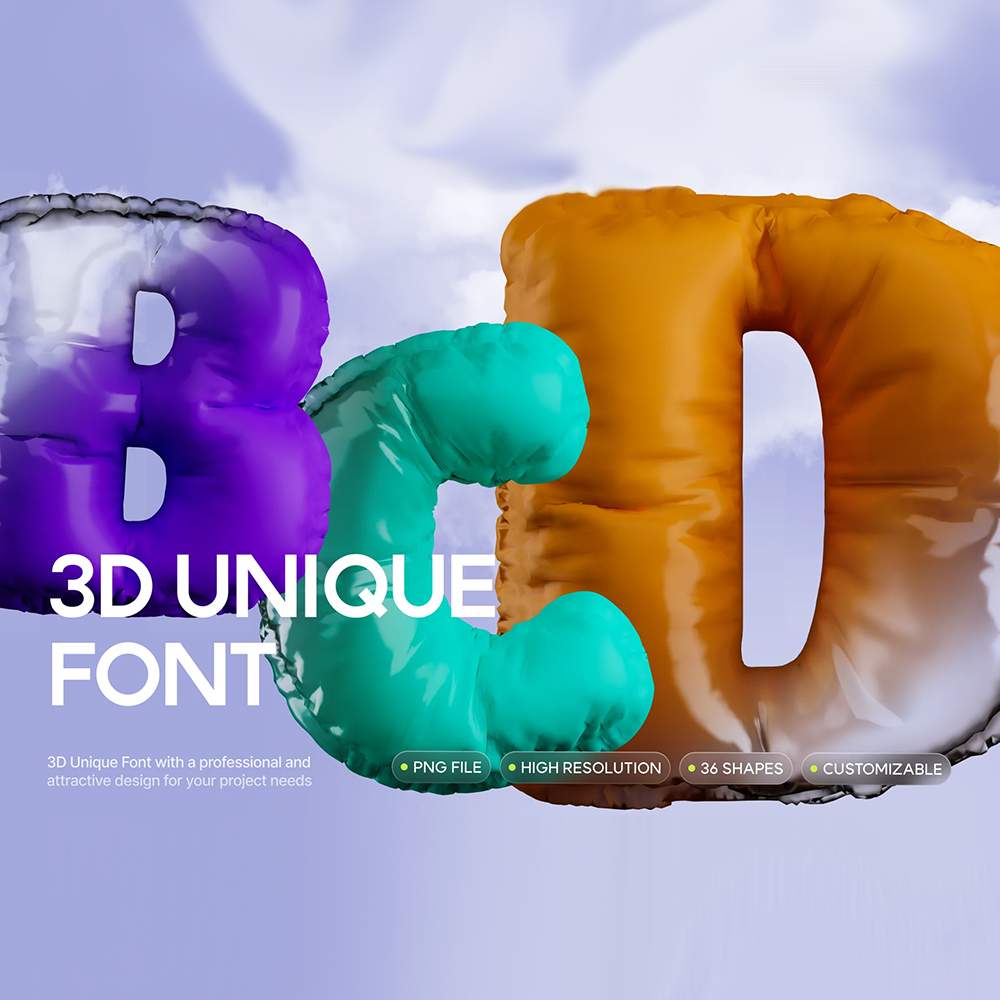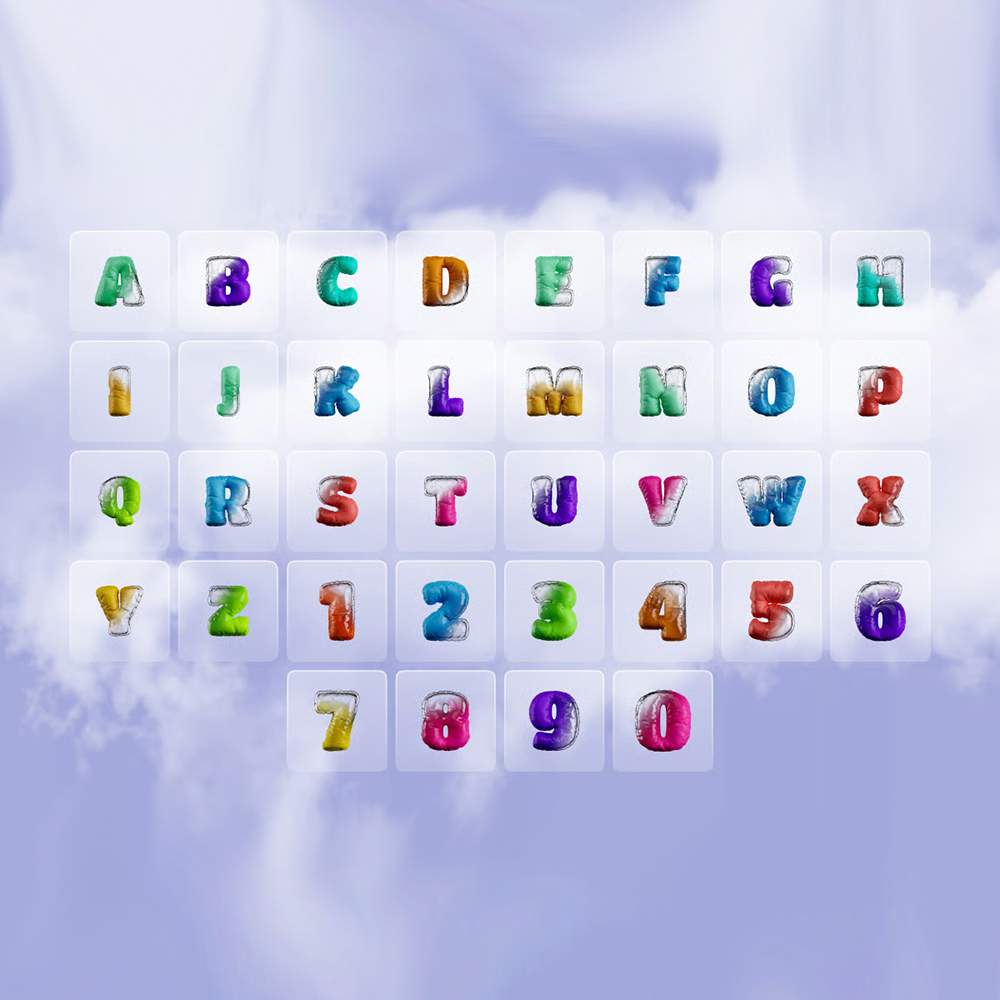
مجموعه منحصر به فرد فونت های سه بعدی
مجموعه فونتهای سهبعدی منحصر به فرد، جلوهای خاص به طرحهای خود ببخشید! این مجموعه فونت شامل ۳۶ عنصر که به شدت کاربردی هستند میباشد و برای جان بخشیدن به پروژه شما و تأثیرگذار کردن آن عالی است. فرمت فونتها PNG می باشند و می توانید آنها را در بسیاری از پروژههای خود به کار ببرید و آنها را با هم ترکیب و مطابقت دهید تا طرحی چشمنواز ایجاد کنید.
مزایای استفاده از این مجموعه فونت چیست؟